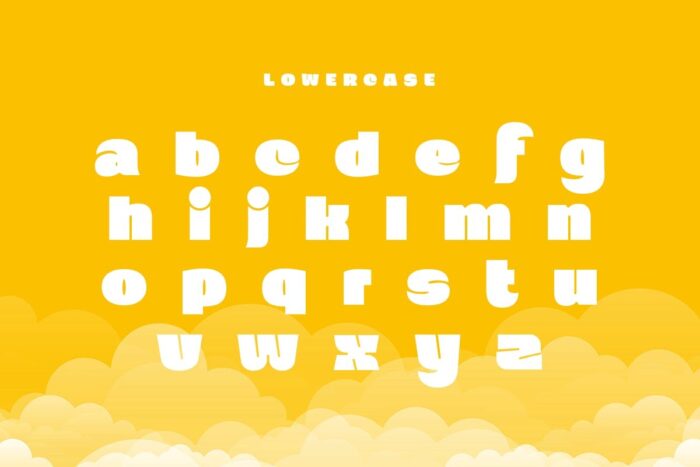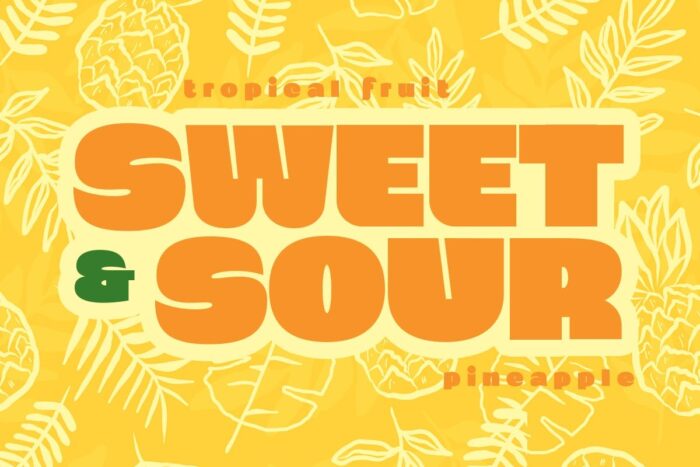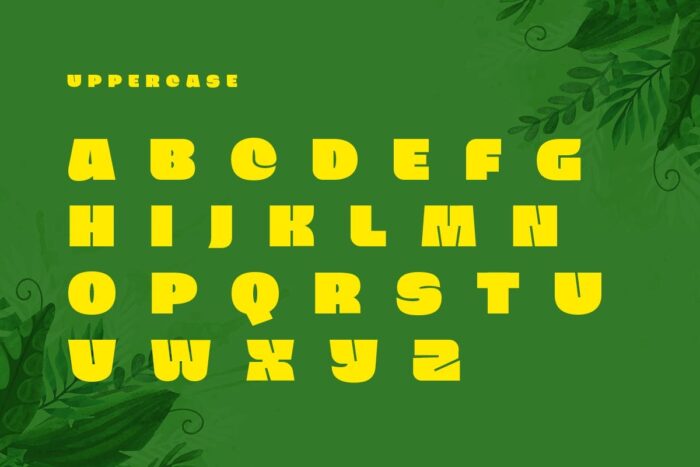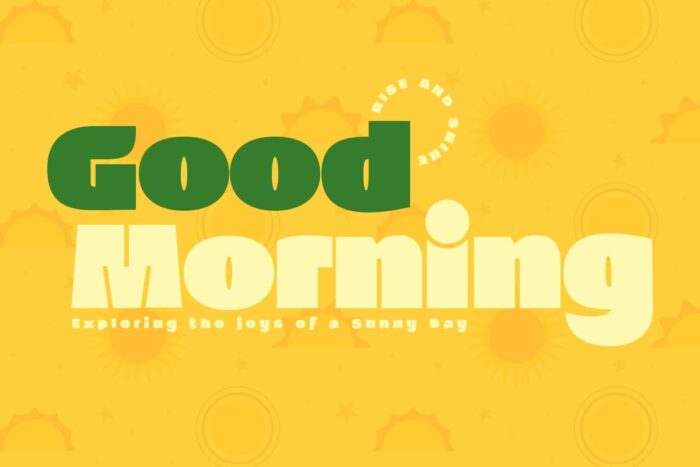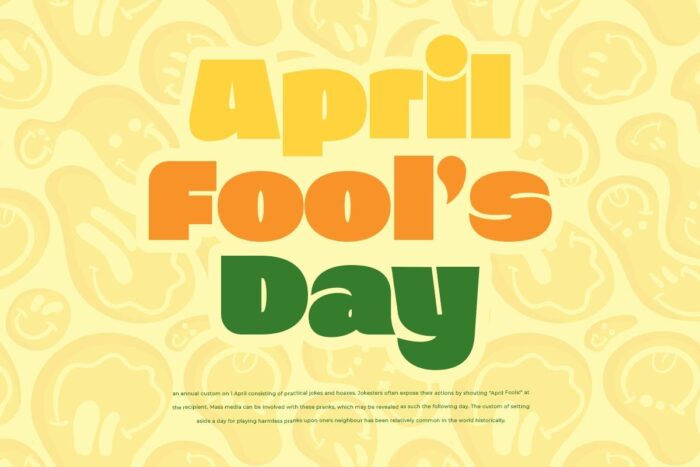
DVN Playing Display Việt hóa – Font chữ trẻ em, vui tươi và ngộ nghĩnh
Playing là một font chữ hiển thị sáng tạo, mang phong cách vui tươi và cổ điển. Font chữ này có các ký tự đậm và tròn trịa, tạo cảm giác thân thiện và dễ gần. Với các đường nét mềm mại và độ dày đều đặn, Playing toát lên vẻ năng động và hứng khởi, phù hợp với các thiết kế cần sự trẻ trung và sinh động.
Phong cách của Playing là sự kết hợp giữa cổ điển và hiện đại, mang lại cảm giác hoài niệm nhưng không kém phần mới mẻ. Sự pha trộn này làm cho font chữ trở nên lý tưởng cho các dự án thiết kế như poster, tiêu đề, logo, và các ấn phẩm quảng cáo. Đặc biệt, Playing rất phù hợp với các chủ đề liên quan đến thực phẩm, đồ chơi, và các sản phẩm dành cho trẻ em nhờ vào vẻ ngoài vui tươi và bắt mắt.
Ứng dụng của Playing rất đa dạng, từ thiết kế đồ họa, in ấn, đến thiết kế web. Font chữ này chắc chắn sẽ tạo điểm nhấn độc đáo và thu hút sự chú ý của người xem.